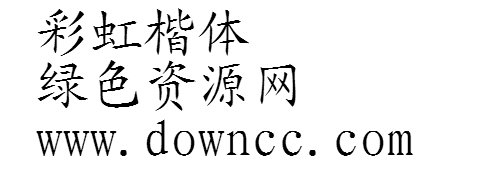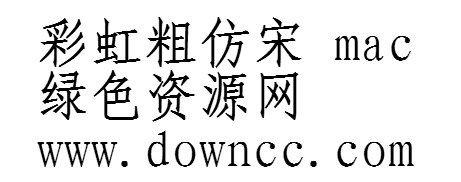
彩虹字體打包是一款匯聚了彩虹小標(biāo)宋/粗仿宋/黑體/楷體四款字體的文件ttf,讓用戶在office辦公中可以更好引用各類字體,讓你的word或excel排版更加大氣穩(wěn)重,綠色資源網(wǎng)今日推薦!
彩虹字體包括彩虹小標(biāo)宋、彩虹粗仿宋、彩虹黑體和彩虹楷體,用于正規(guī)的文稿排版。
在我國大多數(shù)企事業(yè)單位里,撰寫公文必須要使用仿宋字體,